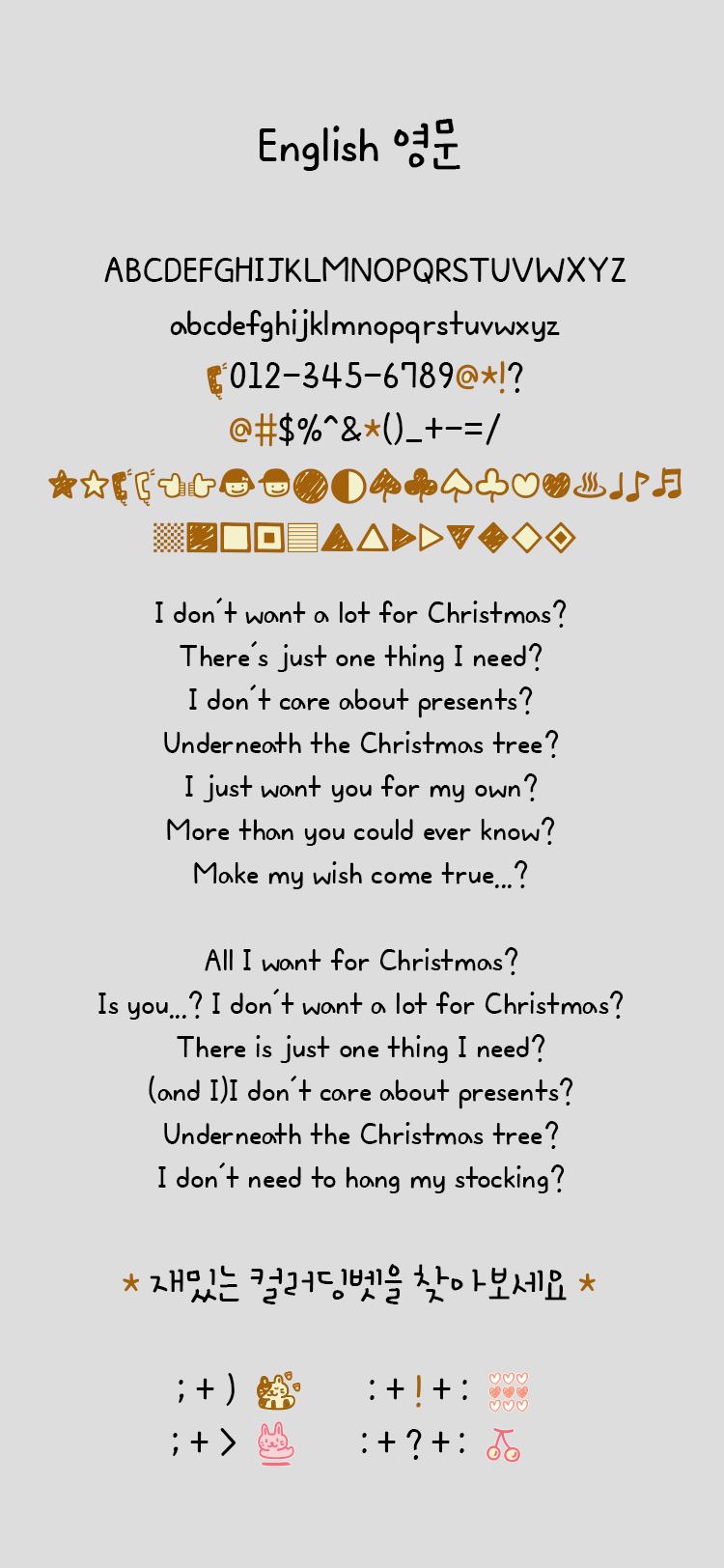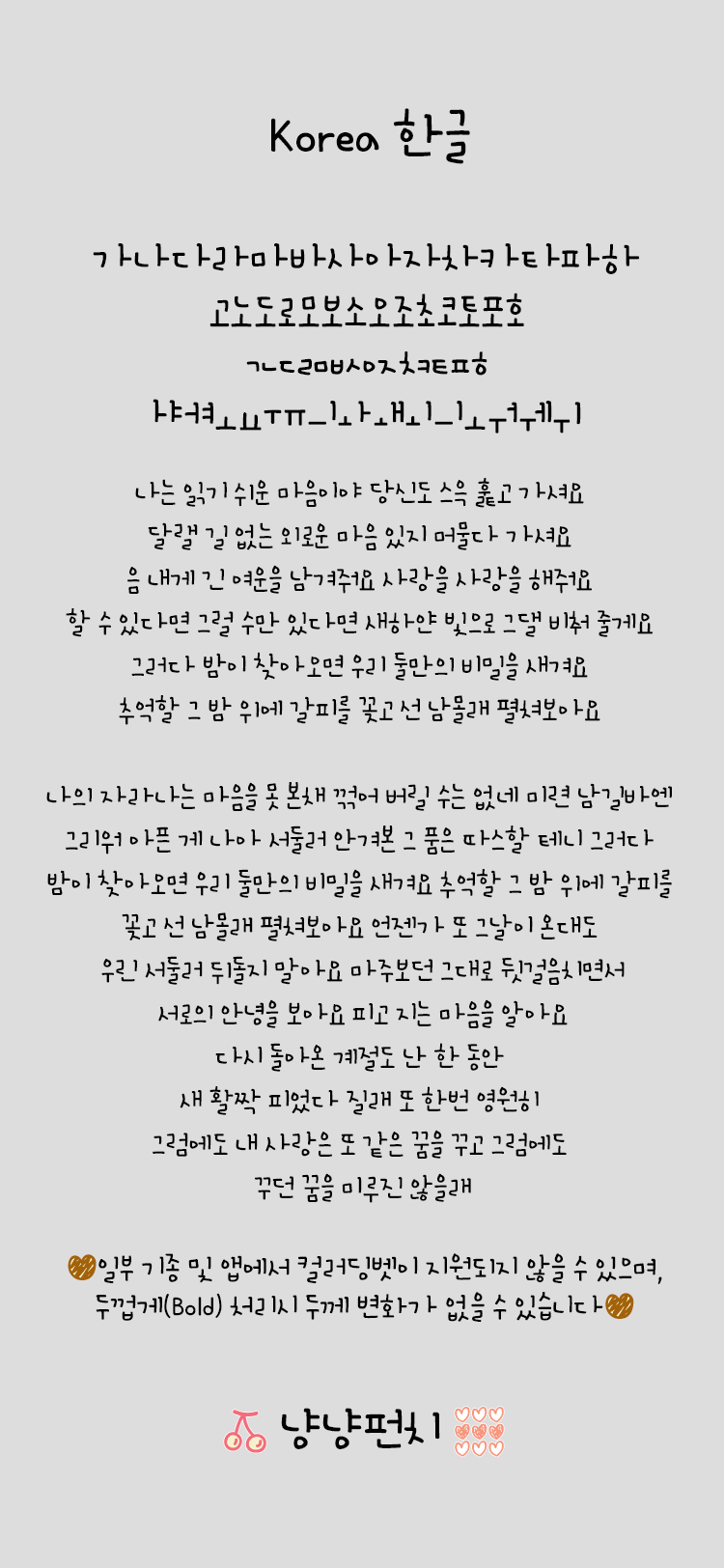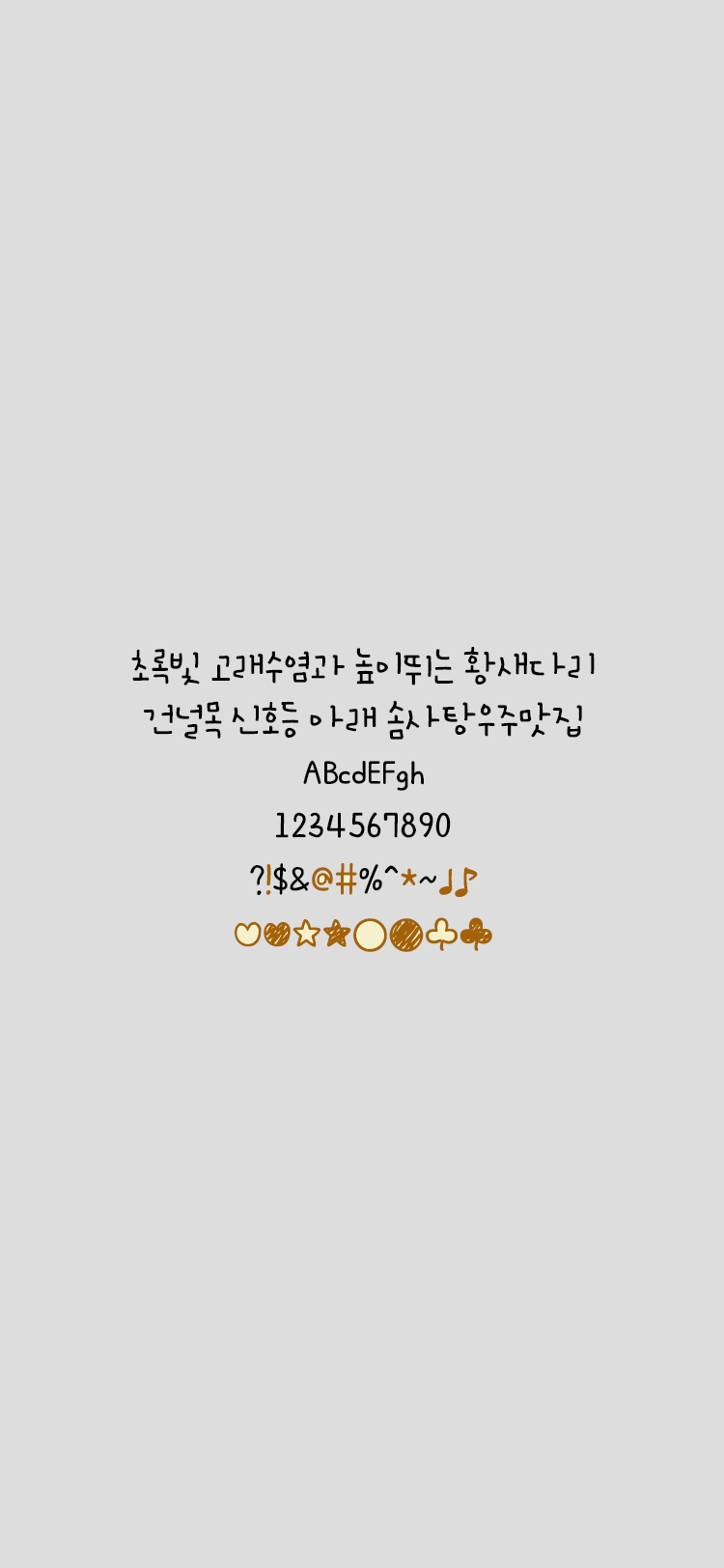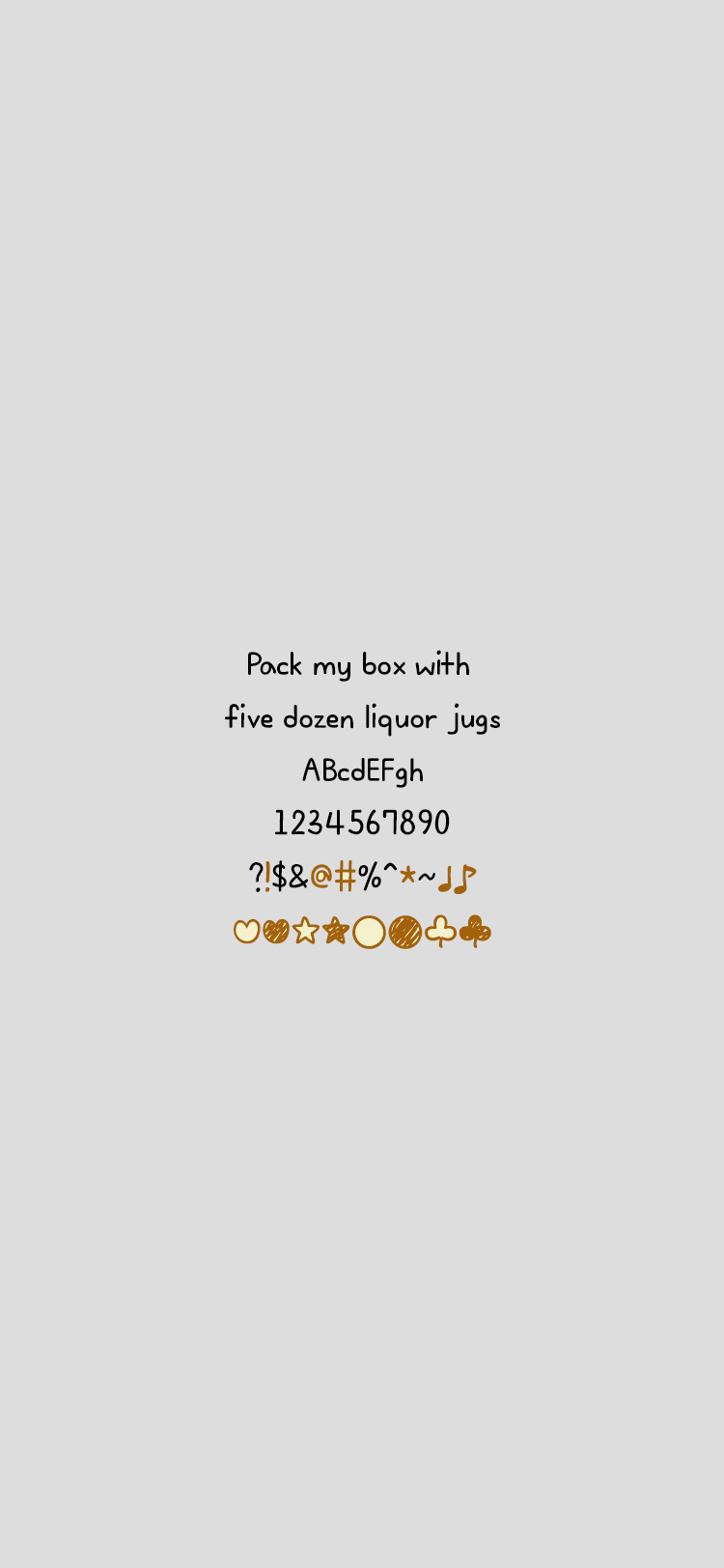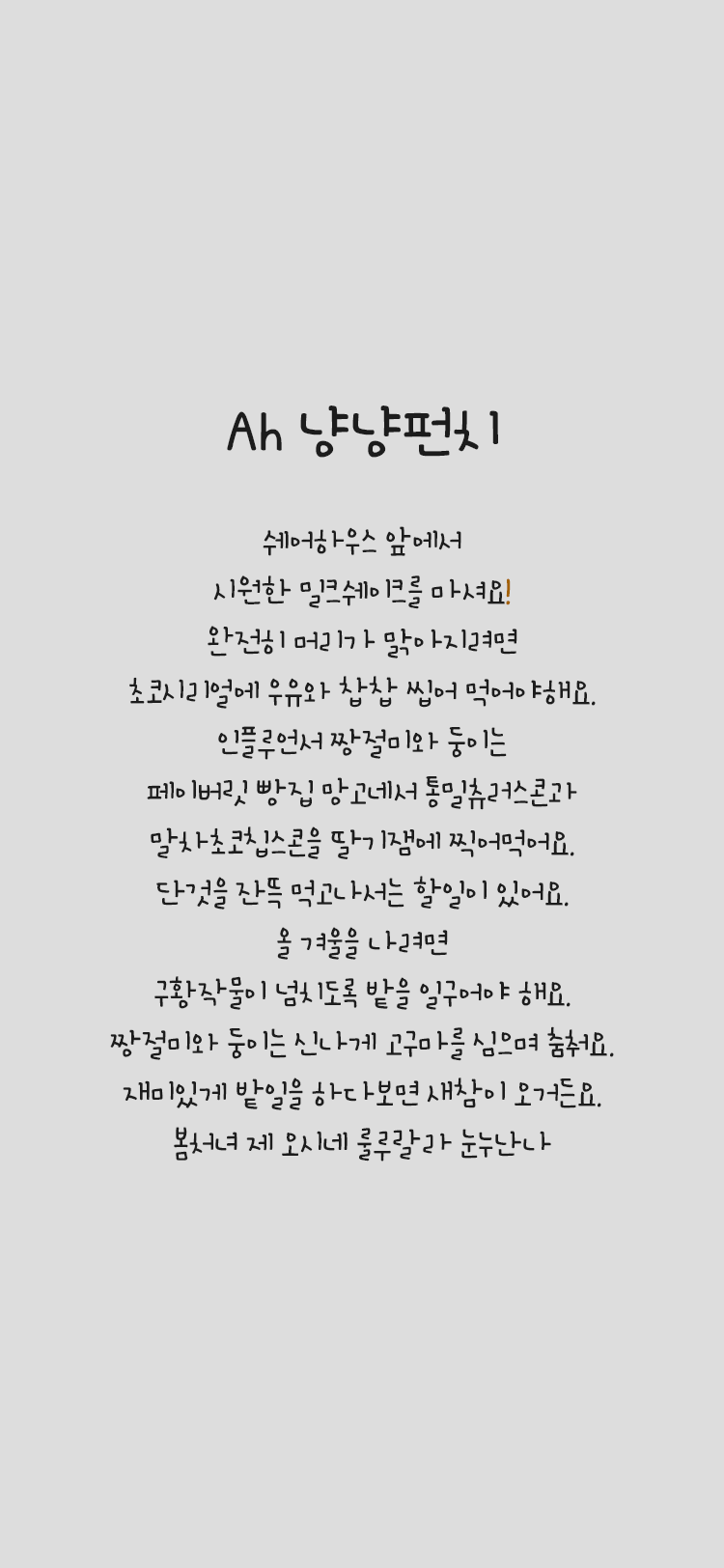
Ah냥냥펀치
이 서체는 자소들을 손으로 또박또박 쓴듯하면서도 자연스러운 형태가 특징입니다.
글줄은 중하단으로 시각적 흐름으로 설정하여 가독성 또한 장문으로 사용 시에도
무리 없도록 제작 하였습니다.
특별한 히든딩벳이 숨어져 있으니 찾아보시기 바랍니다. :>
• 한글 11,172자 / 라틴 95자 / 부호 985자
• 손글씨
• Ah냥냥펀치 / Ah PunchPunch